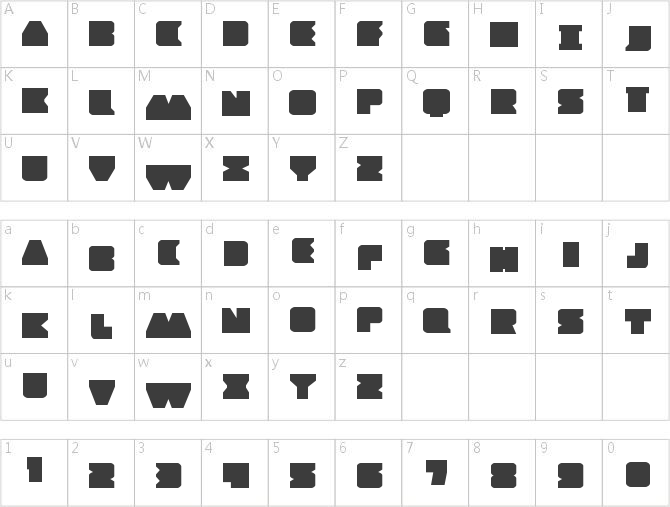
字體名稱: contour
contourofdutyexpand
contourofdutyexpand字體字庫是一款讓人賞心悅目、百看不厭的英文字體,適合各類廣告和產(chǎn)品包裝設(shè)計(jì)應(yīng)用,字體大小0.02MB,格式為ttf字體,上傳用戶是韓國露韓,作者/版權(quán)方為未知